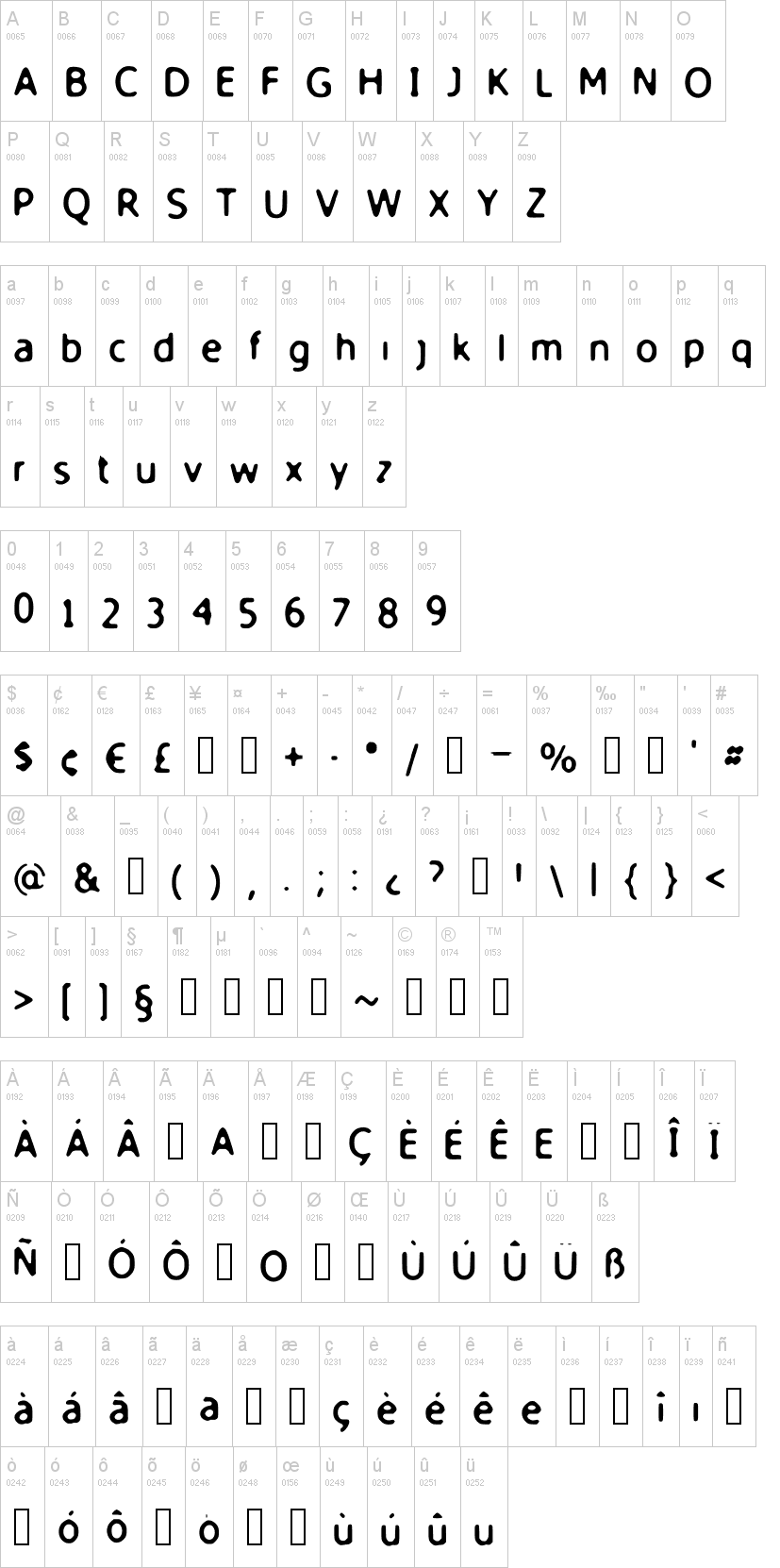
Youm 字体是一款拉丁文字体,由著名的设计师斯特凡·德·布兰克(Stefan de Bruijn)设计,于2004年推出。Youm字体以细节丰富的设计而闻名,采用精致的曲线和温柔的曲线,体现出优雅和流动的特点。它可以用于几乎所有的拉丁文字体,包括英语,法语,德语,西班牙语,意大利语,葡萄牙语,瑞典语,荷兰语,芬兰语,丹麦语,挪威语,希腊语,拉脱维亚语,波兰语,乌克兰语,捷克语,斯洛伐克语,爱沙尼亚语,罗马尼亚语,保加利亚语,拉丁文,爱尔兰文等。Youm 字体具有明显的视觉冲击力,可以用于一些特殊的设计,以及品牌标识,广告,网站,书籍等。内容介绍
Youm是一款非常不错的手写艺术字体,具有很好的视觉感,适合于文化类的宣传设计、商业类品牌的广告和产品包装设计以及个性化文字排版等较多场景。